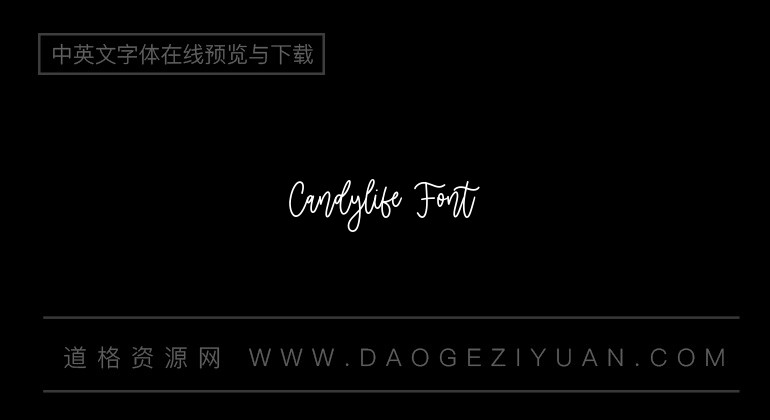
Candylife Font 是一款可爱、甜美的手写风格字体。该字体的字形流畅,适合用于卡通、插画、儿童读物、广告或产品包装等领域。其字母间隙略微拉宽,使得阅读更加舒适。该字体包含了大写字母、小写字母、数字和标点符号,支持英文、西班牙语、葡萄牙语、德语、法语、荷兰语、瑞典语、丹麦语、挪威语和芬兰语等多种语言。Candylife Font 字体的使用范围广泛,可以用于海报、贺卡、logo 设计、网页设计等。内容介绍
Candylife Font是一款非常不错的手写艺术字体,具有很好的视觉感,适合于文化类的宣传设计、商业类品牌的广告和产品包装设计以及个性化文字排版等较多场景。